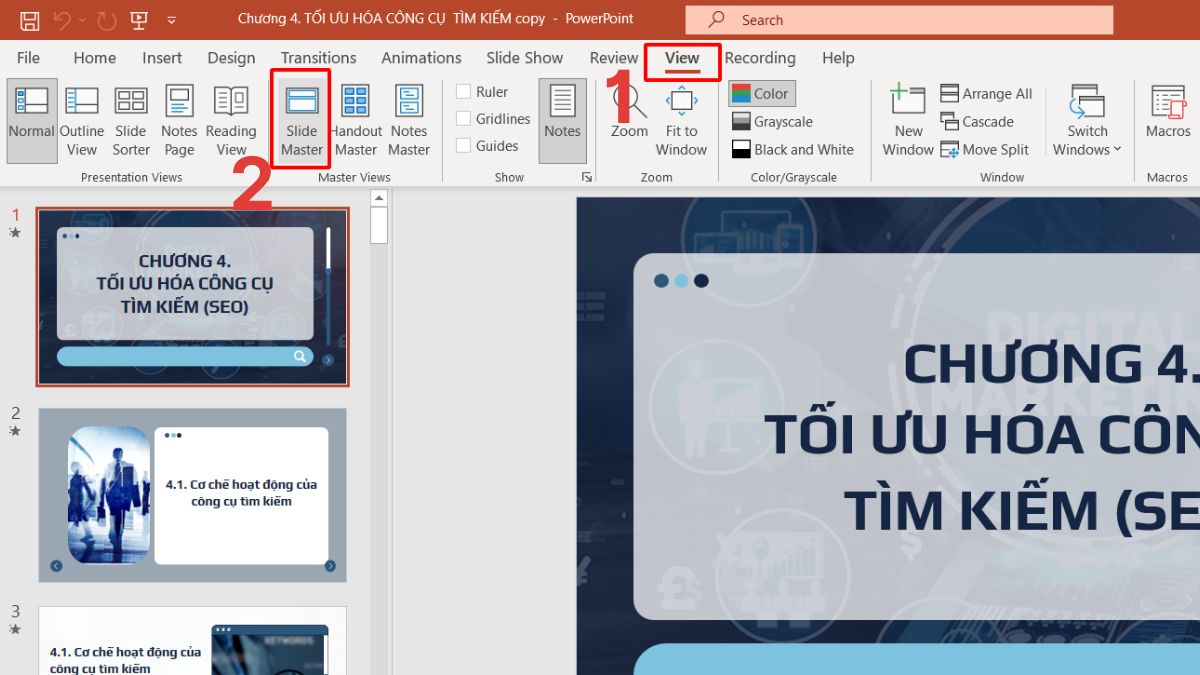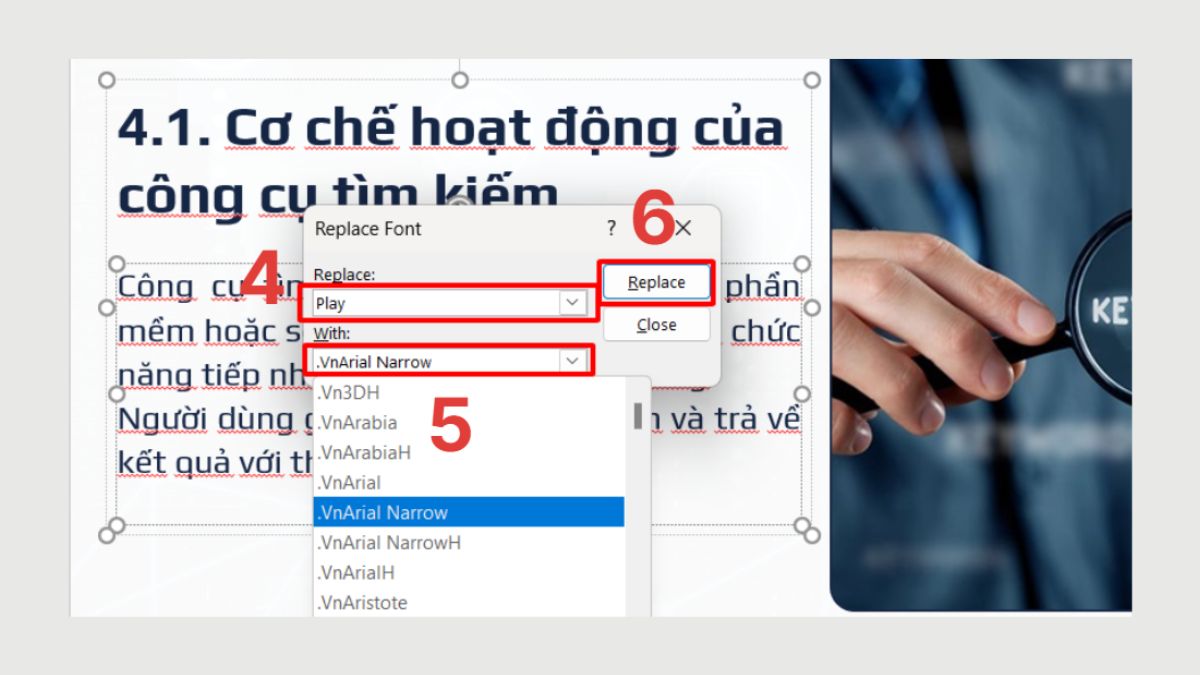
Cách chỉnh font chữ cho tất cả slide trong PowerPoint dễ dàng
Cách chỉnh font chữ cho tất cả slide trong PowerPoint giúp bạn đồng bộ kiểu chữ nhanh chóng, tiết kiệm thời gian khi thiết kế bài thuyết trình. Việc áp dụng cùng một font cho toàn bộ slide mang đến sự chuyên nghiệp và thống nhất, giúp người xem dễ theo dõi nội dung. Cùng tìm hiểu cách đổi font chữ cho tất cả slide một cách nhất quán qua bài viết sau.
Các cách chỉnh font chữ trong PowerPoint nhanh chóng
Để bài thuyết trình đồng bộ và đẹp mắt, bạn cần biết cách chỉnh font chữ cho tất cả slide trong PowerPoint. Dưới đây là các phương pháp đơn giản giúp bạn thay đổi kiểu chữ trong slide chỉ trong vài bước.
Sử dụng Slide Master
Tính năng Slide Master cho phép người dùng thay đổi định dạng chỉ một lần cho tất cả slide qua các bước sau:
- Bước 1: Mở file thuyết trình PowerPoint và vào View > Slide Master.
- Bước 2: Chọn Slide Master đầu tiên (slide lớn nhất trong danh sách bên trái).
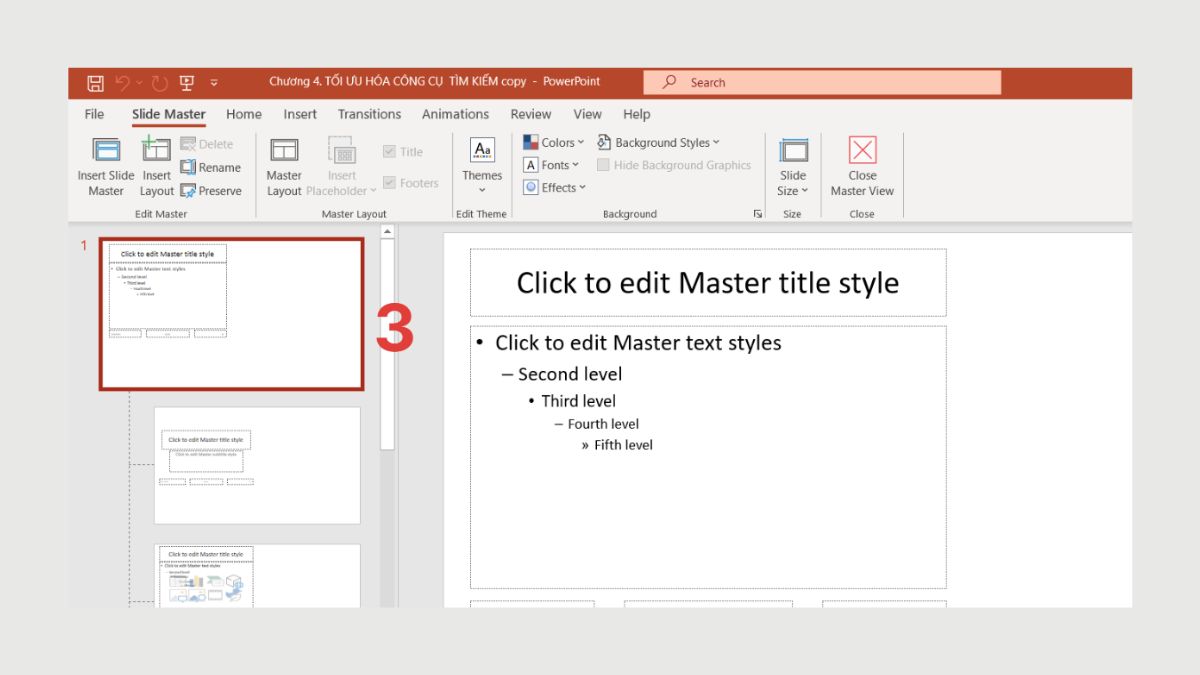
- Bước 3: Bôi đen văn bản và chọn font chữ mới ở mục Fonts.
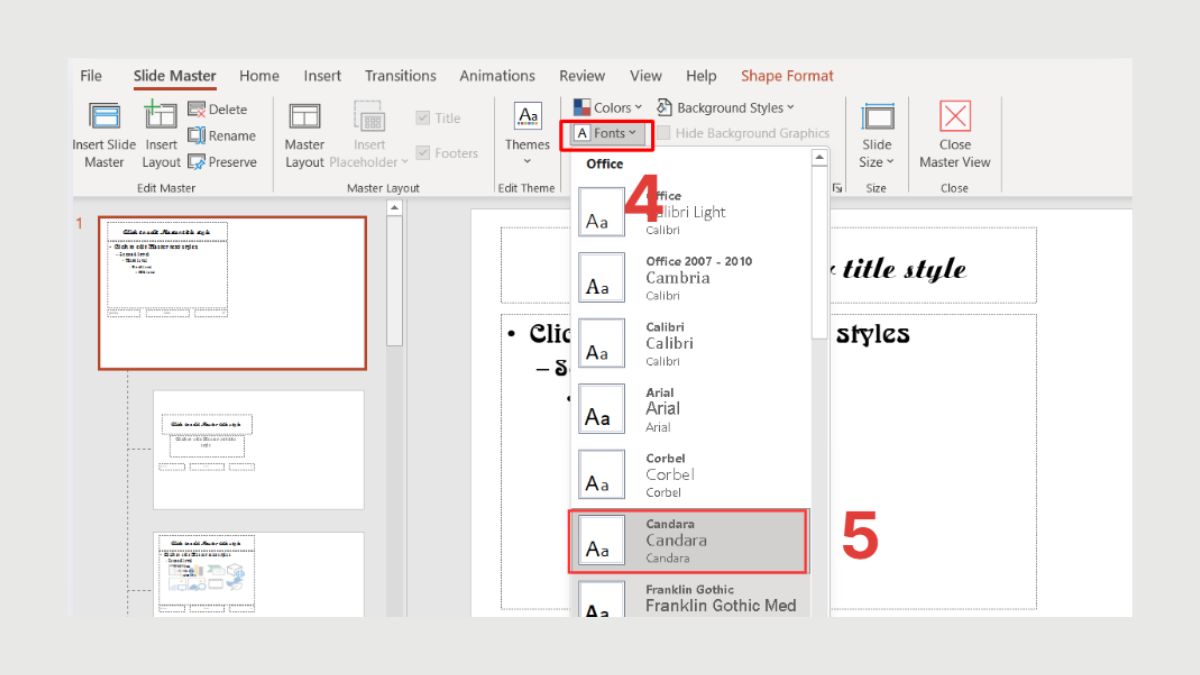
- Bước 4: Quay lại tab Slide Master -> chọn Close Master View để lưu và áp dụng cho tất cả slide.
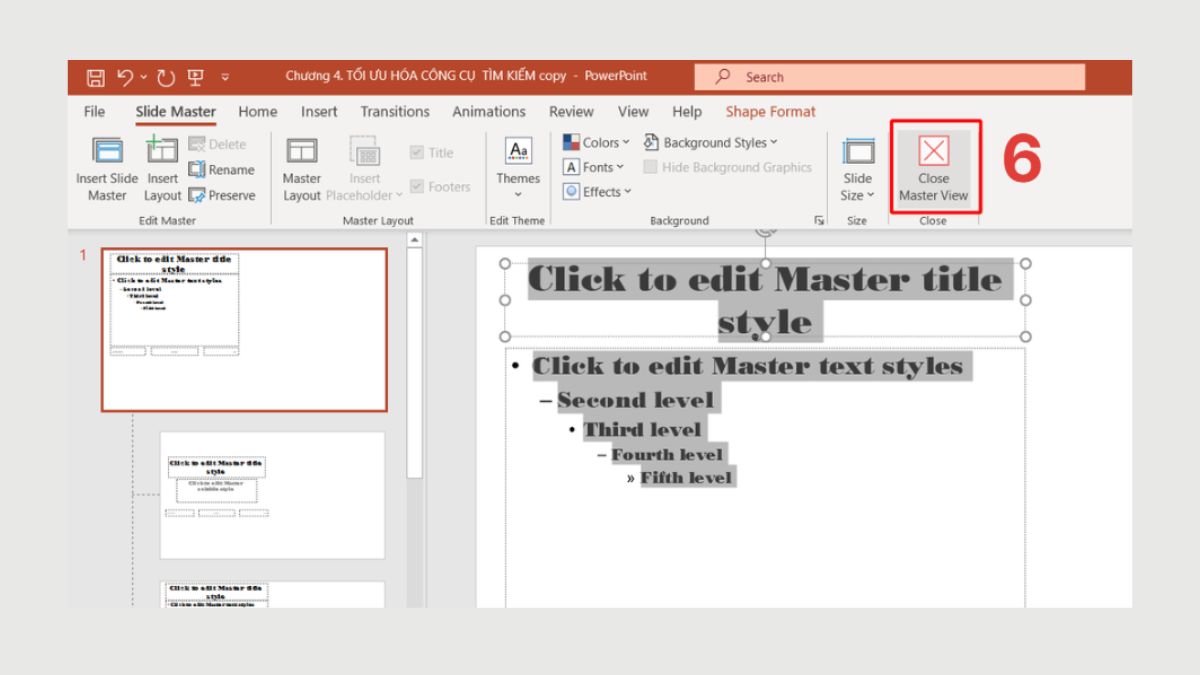
Sử dụng Replace Fonts
Khi bạn muốn đổi toàn bộ phông chữ đã dùng sang một font khác, bạn cũng có thể áp dụng tính năng Replace Fonts như sau:
- Bước 1: Vào tab Home, chọn mũi tên cạnh Replace > Replace Fonts.
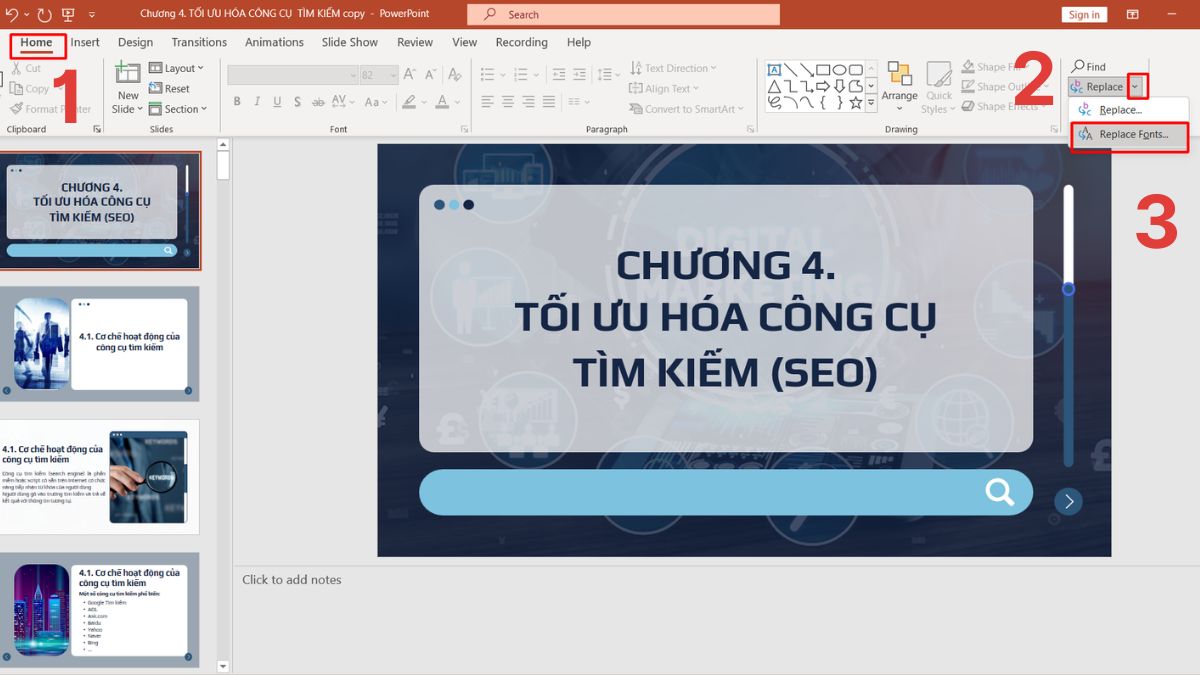
- Bước 2: Chọn font hiện tại ở mục Replace và font mới ở mục With.
- Bước 3: Nhấn Replace để hoàn tất.
Những lưu ý khi chỉnh font chữ trong PowerPoint
Trước khi áp dụng cách chỉnh font chữ cho tất cả slide trong PowerPoint, bạn nên nắm rõ một số điểm quan trọng để tránh lỗi hiển thị. Những lưu ý sau sẽ giúp bạn đảm bảo chữ hiển thị đẹp trên mọi thiết bị.
Sử dụng font chữ dễ đọc
Khi áp dụng cách đổi font chữ trong PowerPoint cho tất cả slide, bạn nên ưu tiên các kiểu chữ đơn giản và rõ ràng. Font quá cầu kỳ không chỉ gây khó đọc mà còn dễ làm khán giả mất tập trung, nhất là trên màn hình lớn. Chẳng hạn, chọn những font phổ biến như Arial, Calibri hoặc Tahoma sẽ giúp nội dung hài hòa và dễ theo dõi.
Không dùng quá nhiều font khác nhau
Khi áp dụng cách chỉnh font chữ cho tất cả slide trong powerpoint, chỉ nên duy trì tối đa từ hai đến ba kiểu chữ cho toàn bộ bài thuyết trình. Việc lạm dụng quá nhiều font khiến nội dung rối mắt và giảm tính thống nhất. Sự thống nhất này mang lại bố cục rõ ràng, khiến thông điệp chính được truyền tải nổi bật và dễ tiếp nhận hơn.
Kiểm tra hiển thị trên thiết bị khác
Sau khi thay đổi phông chữ, đừng quên kiểm tra bài thuyết trình trên các máy tính hoặc màn chiếu khác. Một số font có thể bị lỗi nếu thiết bị không cài sẵn, khiến nội dung hiển thị sai lệch.
Việc kiểm tra trước giúp bạn tự tin trình bày và bảo đảm kết quả của cách đổi phông chữ trong PowerPoint luôn chuẩn xác.
Sử dụng font Unicode để tránh bị lỗi font
Cuối cùng, hãy ưu tiên các font chuẩn Unicode khi chỉnh sửa. Đây là yếu tố quan trọng để cách đổi font chữ cho tất cả slide trong Powerpoint đạt hiệu quả tối đa, vì font Unicode hỗ trợ nhiều hệ điều hành và giảm nguy cơ mất ký tự. Nhờ đó, bài thuyết trình của bạn luôn rõ ràng và thống nhất trên mọi thiết bị.
Cách chỉnh font chữ cho tất cả slide trong PowerPoint giúp bạn đồng bộ kiểu chữ nhanh chóng, tiết kiệm thời gian và tăng tính chuyên nghiệp cho bài thuyết trình. Khi toàn bộ slide sử dụng cùng một font, người xem dễ tập trung và nội dung trở nên rõ ràng hơn. Áp dụng những hướng dẫn trên, bạn sẽ có bản trình chiếu đẹp và nhất quán chỉ trong vài bước.
Câu hỏi thường gặp
Font chữ có bị thay đổi khi mở trên máy khác không?
Có cách nào chỉnh font mặc định luôn là một font cụ thể không?